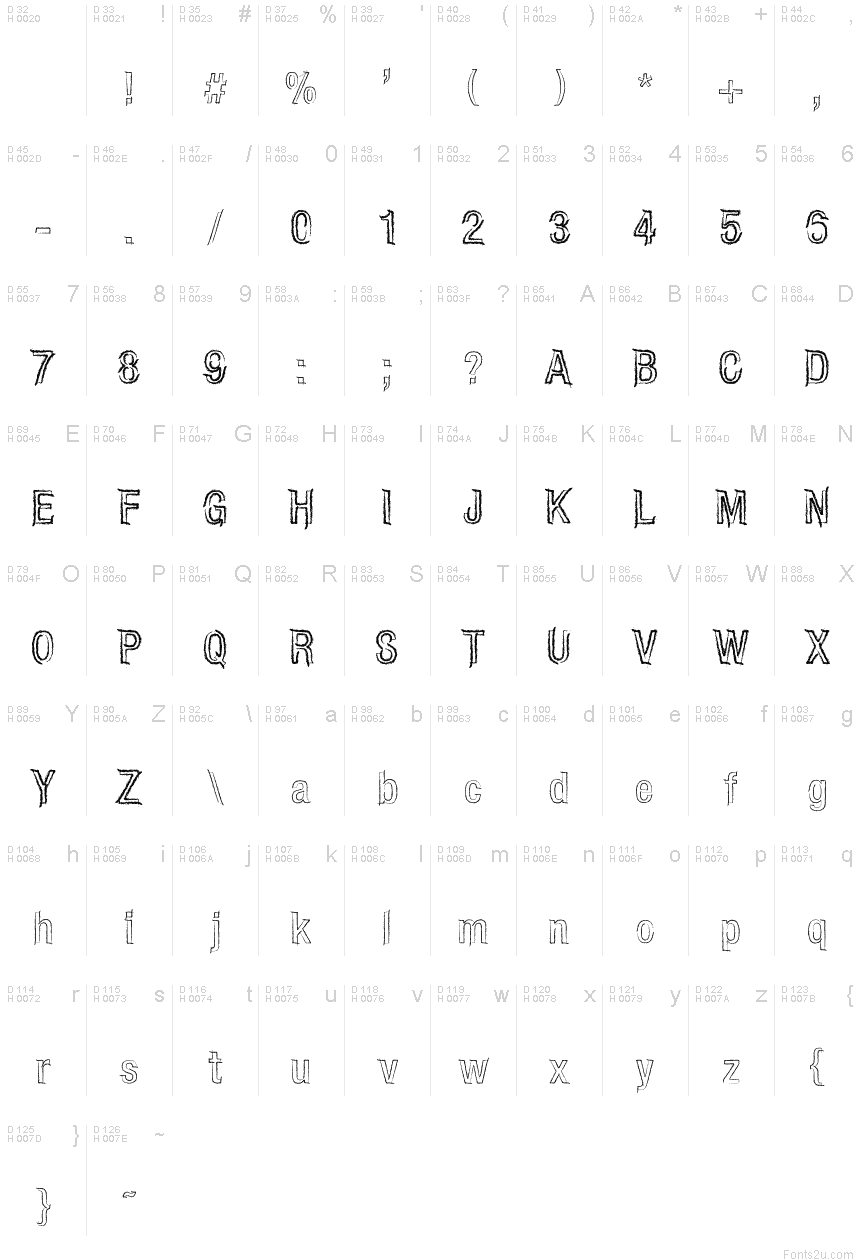
CARBONCILLO PALO  Normal
Carboncillo Palo autorstwa Manuela Lage to darmowy, ręcznie rysowany krój typu display o konturowym wykończeniu, przypominającym szkic węglem. Litery wyglądają na szorstkie i lekko nadgryzione czasem, z drżącymi krawędziami i nierównymi wnętrzami, co nadaje całości charakteru: jest „nabazgrana”, sucha i nieco niepokorna, daleka od wygładzonej, technicznej perfekcji.
Dzięki temu ten darmowy font naturalnie sprawdza się w nagłówkach plakatów, okładkach zinów, oprawie albumów niezależnych, planszach tytułowych, identyfikacji wizualnej w stylu kredowej tablicy czy na krótkich napisach na opakowaniach, gdzie liczy się surowy, ręczny sznyt. Działa świetnie również w inicjałach i krótkich logotypach, ponieważ otwarte, konturowe formy zachowują lekkość, mimo że tekstura jest wyraźna i gęsta.